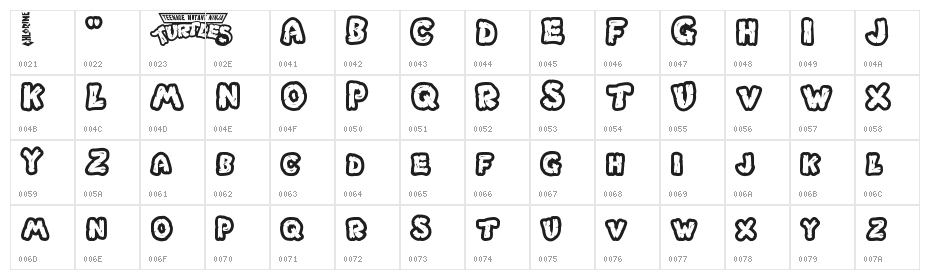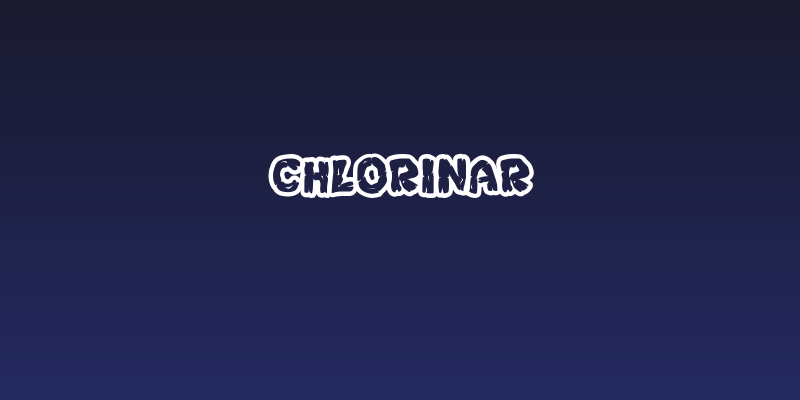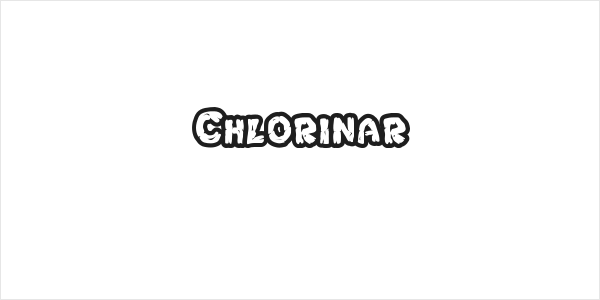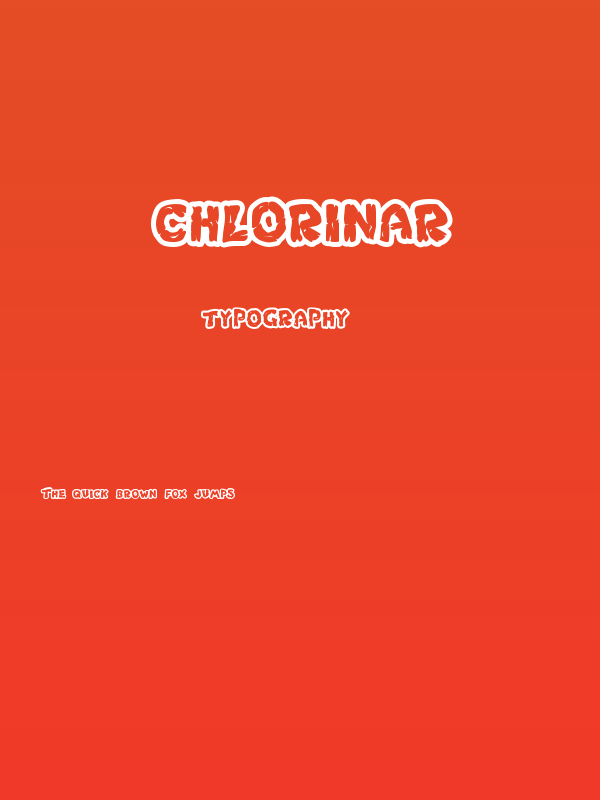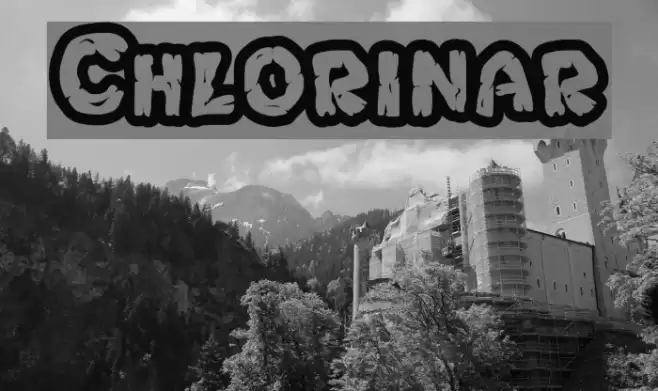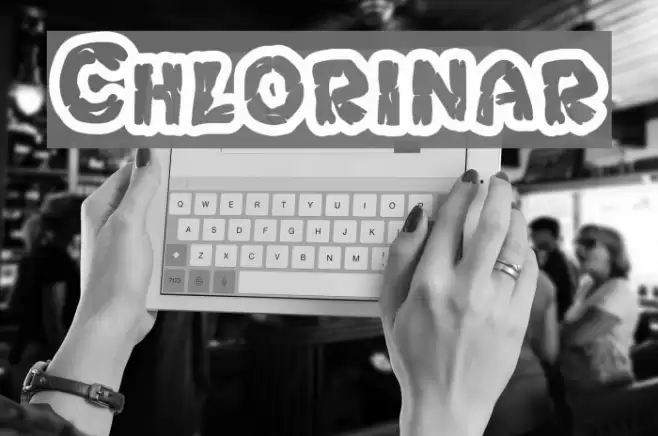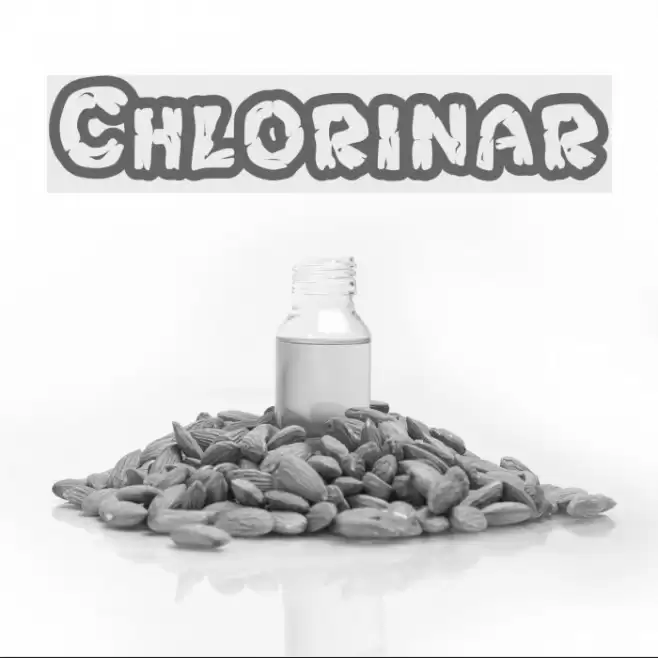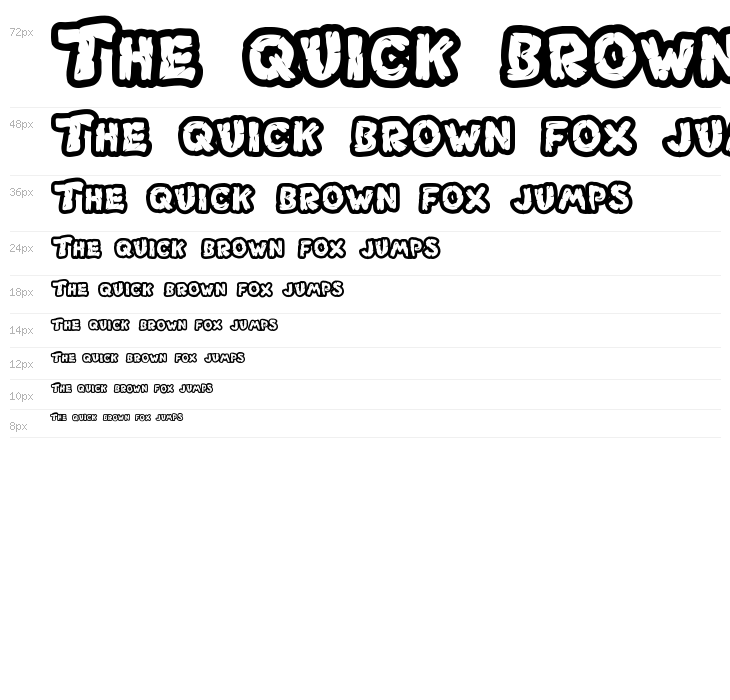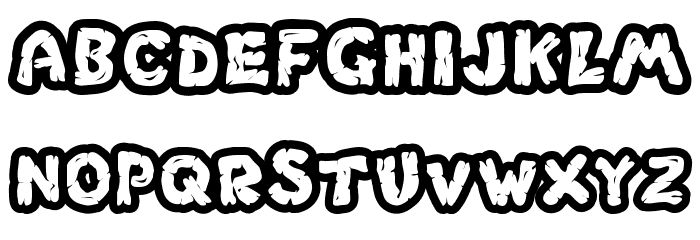
Chlorinar Font
✎ Outline
| Gesamtstil | Playful, Cartoonish |
| Vorgeschlagene Projekte | Ideal for children's books, comic strips, playful branding, and event posters. |